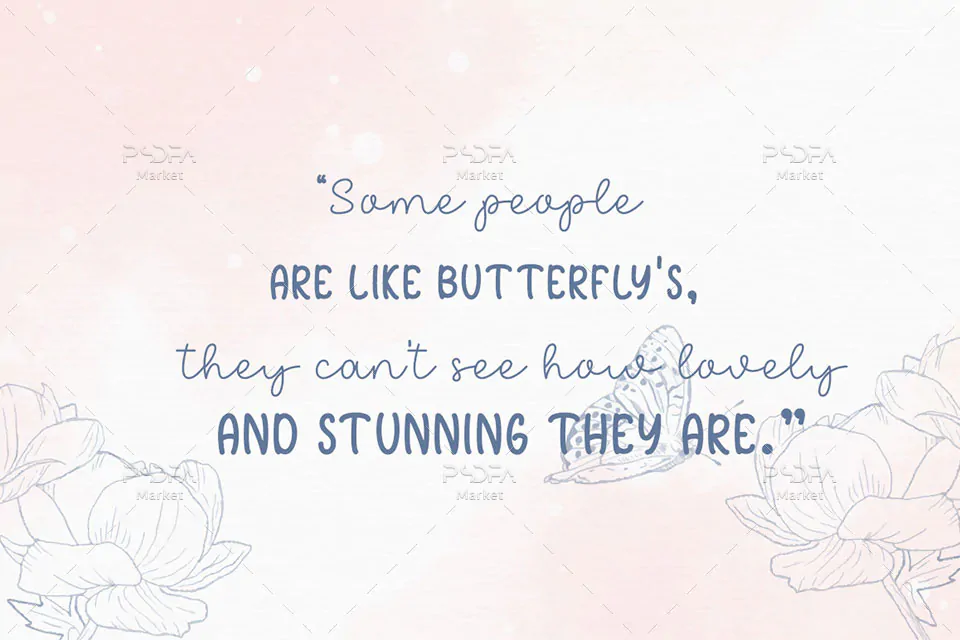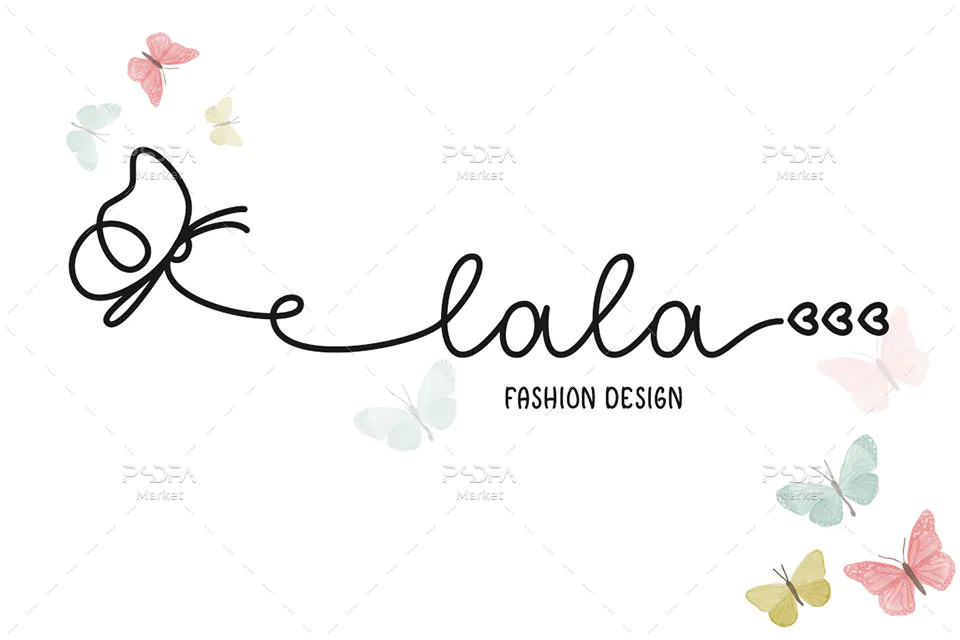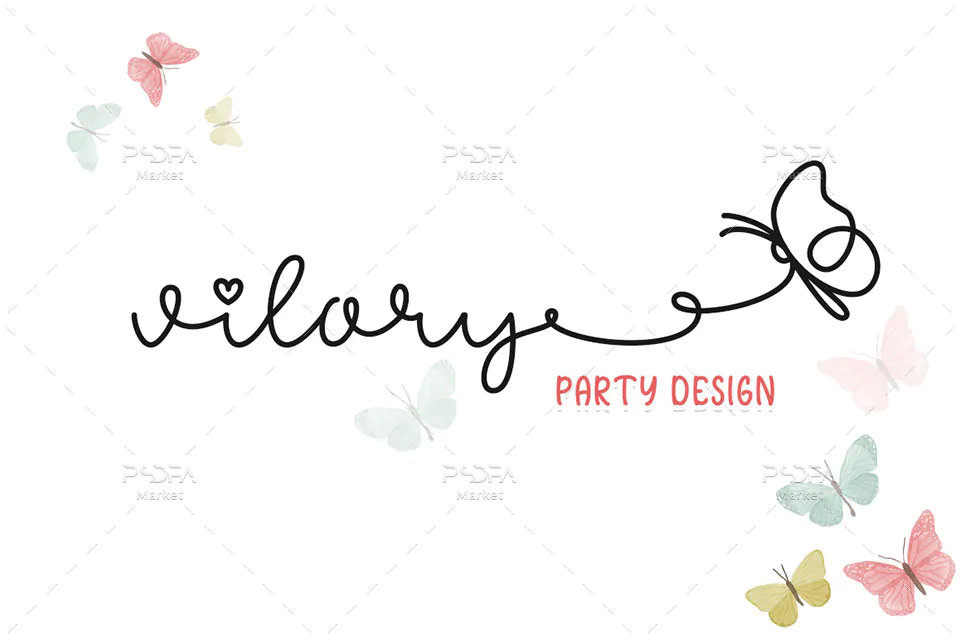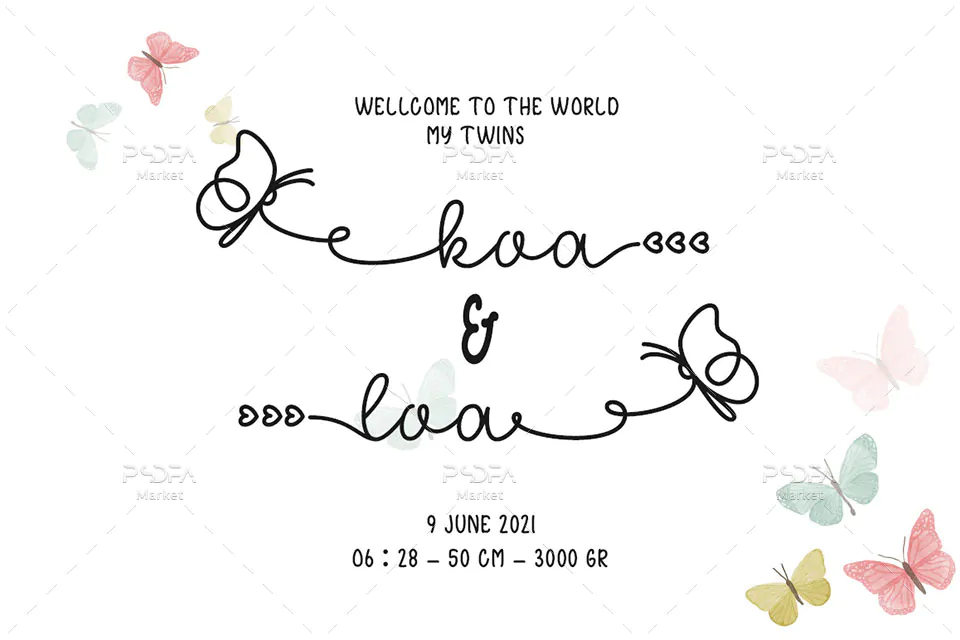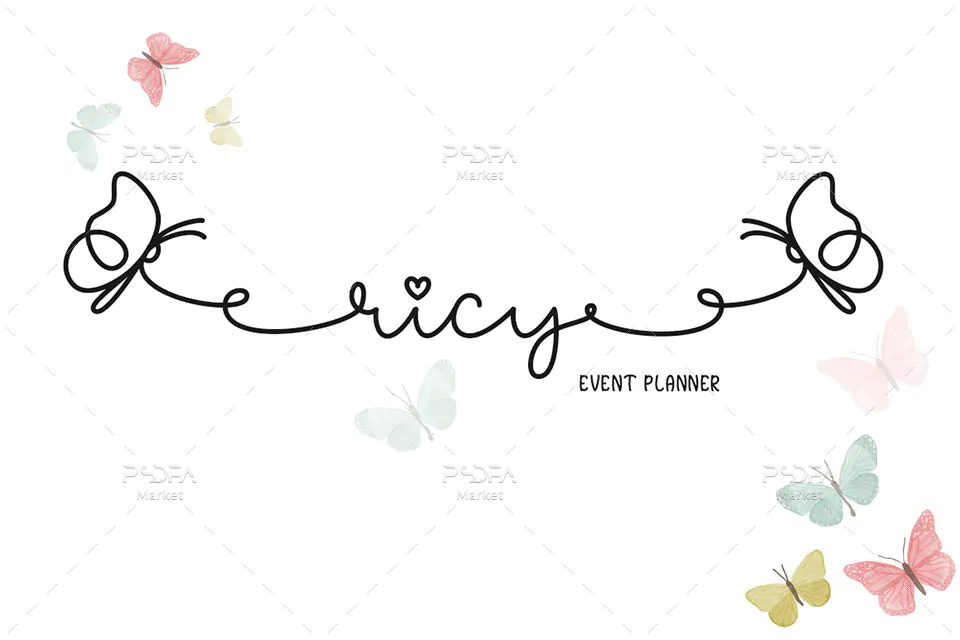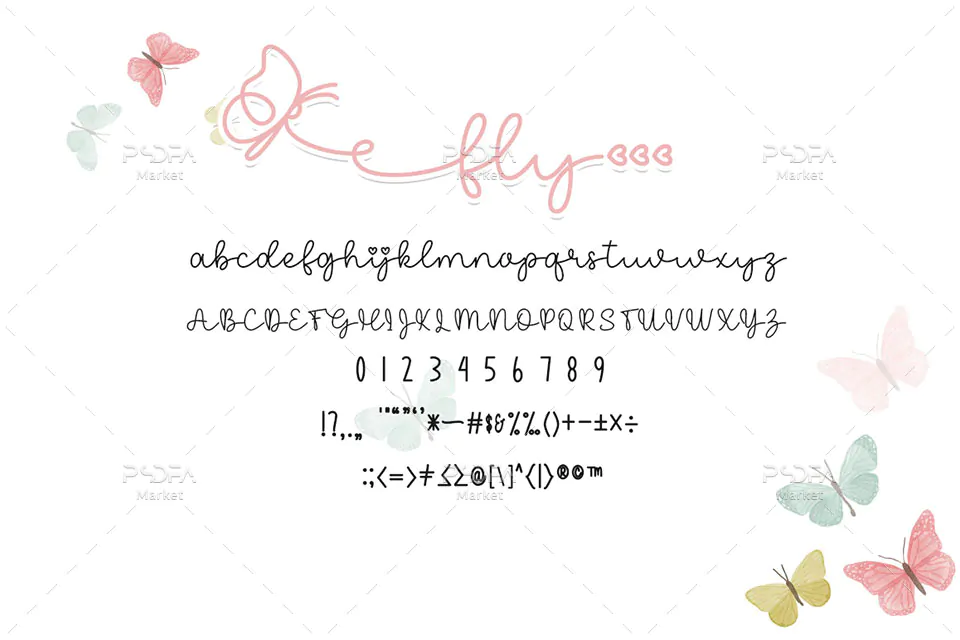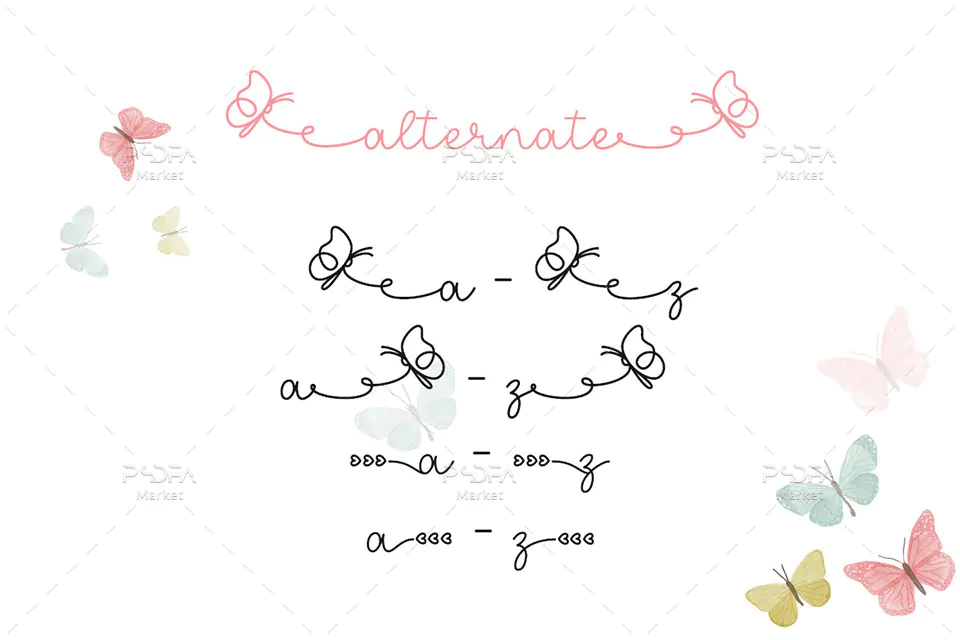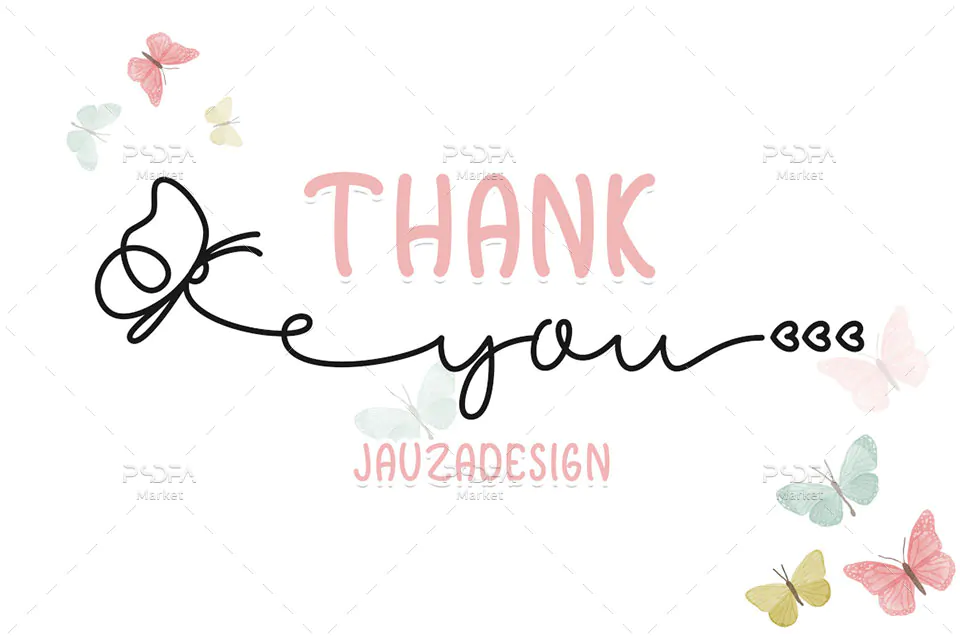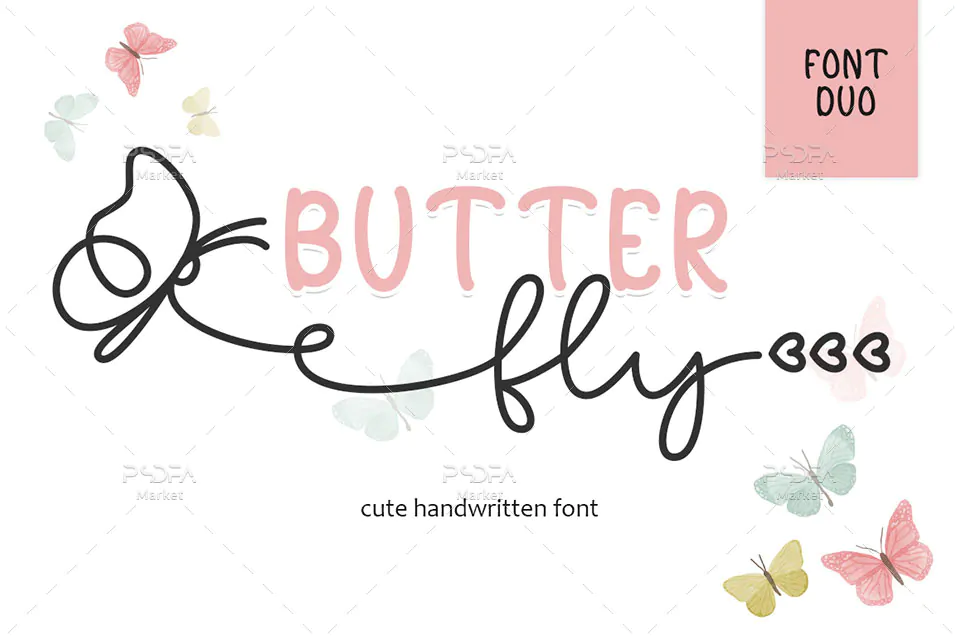
فونت یکسره نویسی و فانتزی پروانه Butter Fly به همراه فونت Fly یک قلم دستنویس فوق العاده زیبای انگلیسی است که مناسب جهت استفاده در طرح و پروژههای گرافیکی مختلف به خصوص طراحی انواع کارت تبریک میباشد. این فونت زیبا در قالب فایل OTF, TTF در فایل محصول قرار دارد که با نصب یکی از این 2 فرمت در پوشه فونتهای سیستم میتوانید از این فونت انگلیسی در تمام نرم افزارهای گرافیکی و تایپ متون همچون فتوشاپ، افتر افکت، پریمیر، ورد، پاورپوینت و … استفاده کنید.
فونت دستنویس و رمانتیک پروانه در وزن معمولی (Regular) طراحی شده است که میتوانید از آن در طراحی انواع کارت تبریک، کارت پستال، بسته بندی محصولات، لوازم التحریر، بگهای خرید و هدیه، ظروف یکبار مصرف، تقویم، پوستر، بنر، بروشور، تراکت و دیگر طرحهای گرافیکی استفاده کنید. همانطور که ذکر شد فونت Fly نیز از همین خانواده در فایل محصول قرار دارد که از آن هم میتوانید در طرحهای خود استفاده کنید.
- نام فونت: Butter Fly, Fly
- وزن: Regular